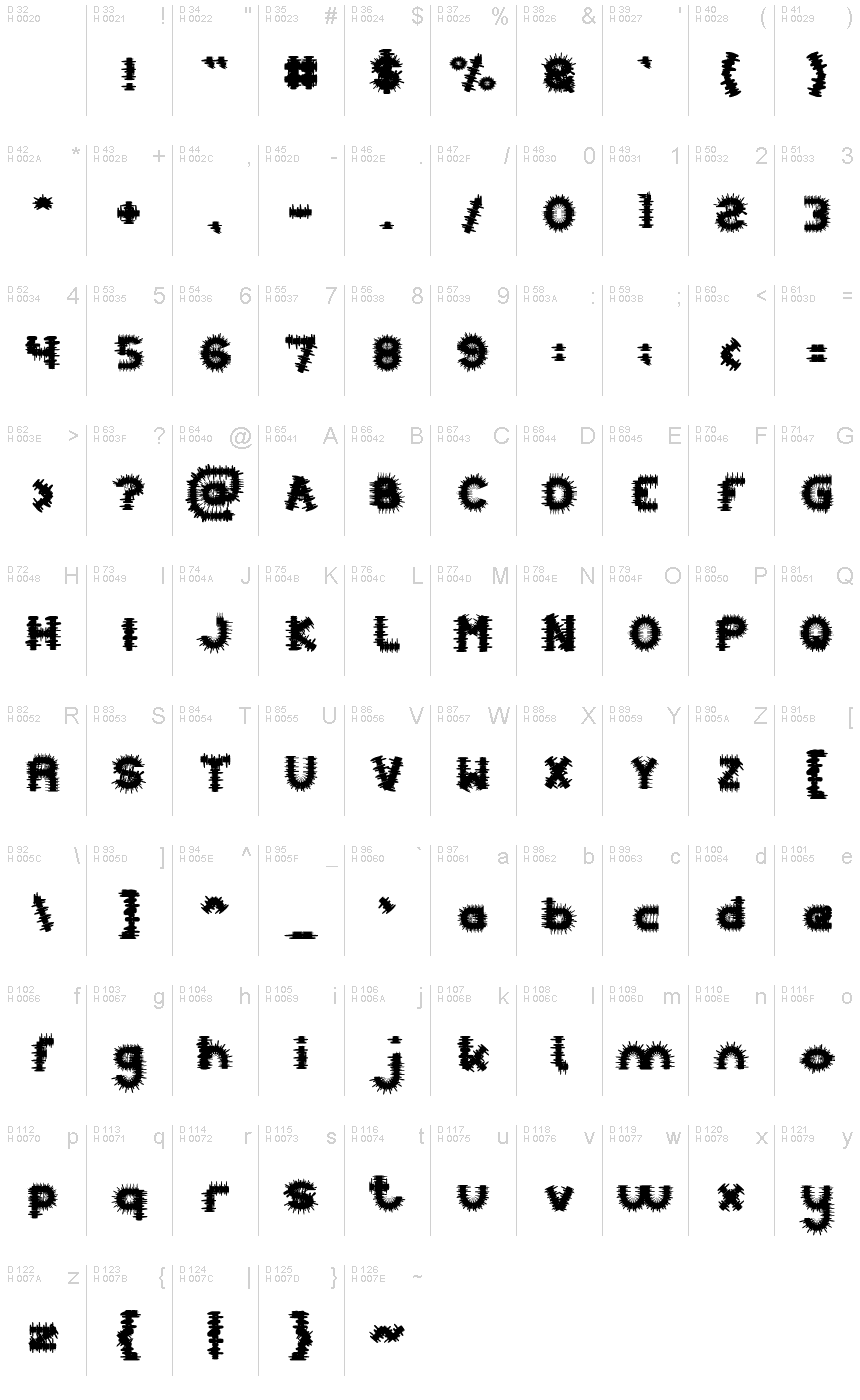
PUNK od Weknow to darmowy, zdeformowany font typu display o buntowniczym, ręcznie robionym charakterze w stylu punk. Litery wyglądają, jakby zostały poskładane z gęstych zadrapań, kolców i nałożonych na siebie pociągnięć, dzięki czemu nawet proste formy wydają się hałaśliwe, szorstkie i nieco niestabilne.
Ta surowa energia świetnie pasuje do plakatów zespołów, okładek zinów, grafik streetwearowych, ulotek imprezowych i tytułów, gdzie liternictwo powinno sprawiać wrażenie naklejonego i na wpół zdartego. Jako darmowy font najlepiej sprawdza się w krótkich nagłówkach, logotypach i monogramach, ponieważ poszarpana tekstura i chaotyczne sylwetki niosą przekaz równie mocno, co same słowa.
PUNK